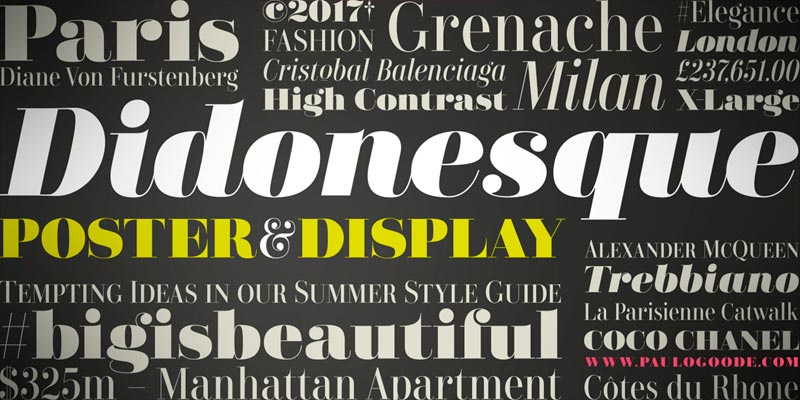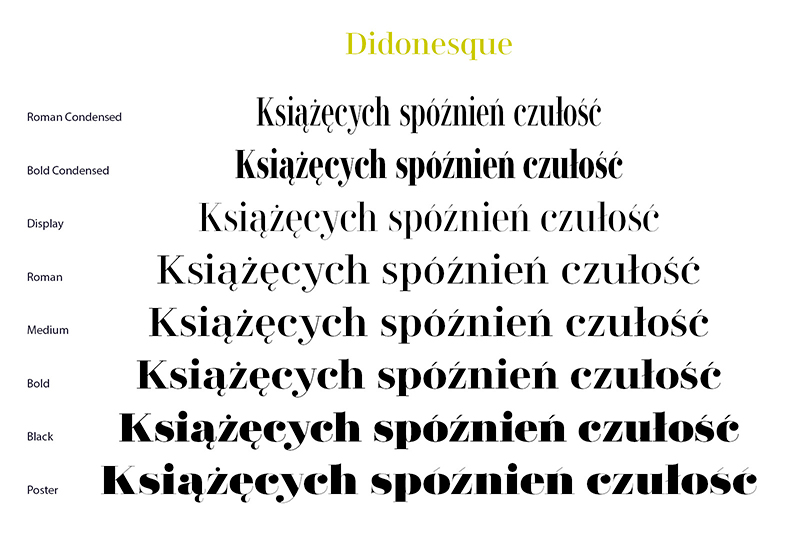
Font Didonesque
Do naszego studia trafił ozdobny i elegancki font Didonesque charakteryzujący się bardzo wysokim kontrastem. Rodzina składa się z 16 odmian.